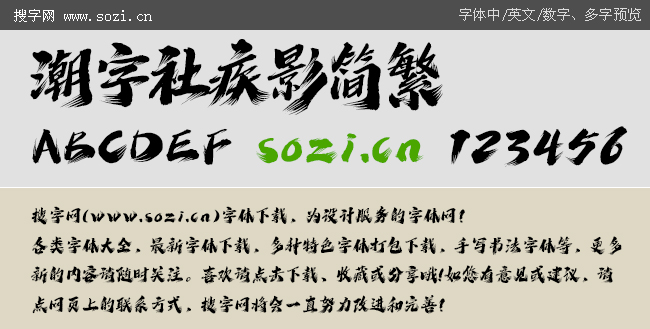
潮字社疾影簡繁
搜字網(wǎng)提供一款潮字社疾影簡繁中文字體下載,潮字社疾影簡繁是一款非常獨特的個性毛筆藝術(shù)字體,這款字體筆觸較為粗實,字體書寫端正大方,適合應(yīng)用于藝術(shù)設(shè)計、平面宣傳設(shè)計、網(wǎng)頁設(shè)計等領(lǐng)域等應(yīng)用。(本字體為個人非商用版,商用請聯(lián)系作者購買授權(quán))